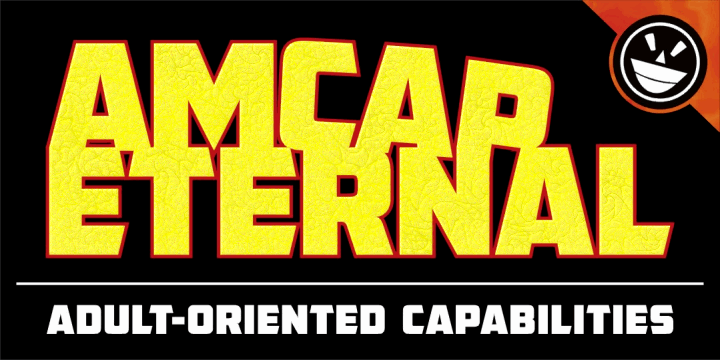
AMCAP Eternal é uma nova adição à ampla gama de fontes sans-serif oferecida pela Hamilton Design Studio. Criada para quem busca uma fonte dinâmica e moderna, AMCAP Eternal captura a essência do American Captain, mantendo seu ar robusto e robusto junto com os sutis toques que tornam este tipo tanto reconhecível quanto versátil. Com linhas finas e claras, AMCAP Eternal oferece uma ótima resposta para qualquer aplicação gráfica moderna. Suas formas curvas fluidas e linhas retas sólidas criam um contraste visual interessante que promete trazer seus projetos para fora da linha do tempo. Esta fonte é especialmente apropriada para aplicações em mídias digitais, web sites e aplicativos devido ao seu peso leve mas forte, garantindo que as letras se destaquem sem comprometer o desempenho online. O designer Hamilton oferece uma versão moderna do American Captain, redefinido para a geração digital atual. AMCAP Eternal não apenas traz um novo olhar para uma fonte clássica, mas também adiciona seu próprio toque único e contemporâneo. Seja você um graphic designer ou um desenvolvedor web, AMCAP Eternal é uma escolha ideal que certamente vai transformar a forma como você cria seus projetos digitais.